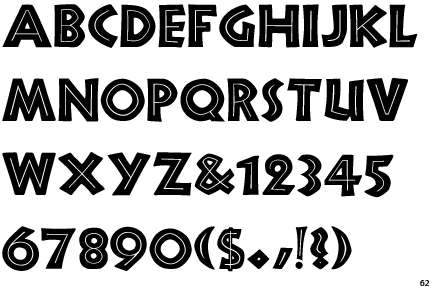
Woher kommt "Afrikanische Schrift"
Es fing an mit einer Packung Chips bei Aldi. Afrikanische Gewürzmischung: Elefanten, Sonnenuntergang... das Übliche. Und diese Schrift! Ich bin selbst kein Typograph, deswegen fehlen mir die Fachvokabeln um sie zu beschreiben... Ohne Serifen, irgendwie "naiv" relativ große Laufweite, generell breites Schriftbild, "gedrungene" Buchstaben, sehr fett und ein weißer Strich in der Mitte. Hier ist ein Beispiel: http://www.identifont.com/samples/monotype-imaging/FFDNeulandInline.gifKennt bestimmt jeder und jeder verbindet diese Schrift mit Afrika (etwas ähnliches wurde schon hier http://www.typografie.info/typoforum/viewtopic.php?f=7&t=2860&p=18009&hilit=afrika#p18009 diskutiert.
Seit dem habe ich die Augen offen gehalten... die Schrift wird überall mit Afrika verbunden, (ich glaube jedenfalls nicht nur in Deutschland) und scheint bereits relativ alt zu sein, auf jeden Fall mindestens 50 Jahre.
Ich frage mich nun: Wie kommt es, dass diese Schrift mit Afrika assoziiert wird? Wo kommt sie her und wann wurde sie von wem erschaffen? Gibt es afrikanische Schriftzeichen, an die das Schriftbild angelehnt ist oder wurde sie komplett erfunden?
Die Neuland wurde 1923 von Rudolf Koch für Gebr. Klingspor geschnitten. Gemeint war sie eigentlich als Schrift mit deutlichem Holzschnittduktus.
Möglicherweise ist es dieses holzschnittartige, grobe, handwerkische, das irgendwann mit Africa assoziiert wurde. Und wenn erst mal einige anfangen, eine Schrift in so eine Ecke zu drängen, dann entwickelt das eine Eigendynamik und die Schrift wird dann auch verstärkt mit dem entsprechenden Subject verbunden. Das ist dann irgendwann pure Sehgewohnheit. Jedenfalls hat sie keine africanischen Wurzeln und Koch wird wohl auch ganz andere Assoziationen damit verbunden haben (siehe auch rechter Teil der obigen Abbildung, das scheint eine originale Koch-Graphik zu sein).
Die Neuland wurde übrigens auch für Jurassic-Park eingesetzt, das hat der Schrift vielleicht auch einen kräftigen Tritt Richtung Dschungel verpaßt.
Was da fehlt ist IIRC der Verweis auf die 1950er in Deutschland. Da erwachte das Interesse an fernen Ländern erneut, diesmal etwas friedlicher und weniger invasiv, aber das Reisen war für die breite Masse noch unerschwinglich. Schon Italien war nur für eine Minderheit erreichbar. Aber es gab viele Bücher und Sammelheftchen zu den fernen Ländern. (Wurde die Verwendung der Neuland wieder re-importiert oder wurde sie schon vorher so verwendet?) Dadurch wurde die Neuland dann auch in Deutschland (und Europa) quasi zum Standard für Afrika, Exotik und Sonne. Sonnenstudios benutzen auch gelegentlich die Neuland.
Ich habe alte Sammelheftchen von meinen Großeltern über Afrika und Südamerika (*) aus den 1950ern mit der Neuland auf dem Titelblatt. Die habe ich als etwa 10jähriger bekommen und wegen der Grafiken und der Schrift aufgehoben.
(*) Indigene Themen: Siehe American Spirit Zigarettenpackung im Bericht.
Sehr interessant! Auf so ein Sammelheftchen bin ich auch gestoßen! Ich glaube, eine Margarine-Firma hat das rausgebracht...
Aus einem der Bücher raus: